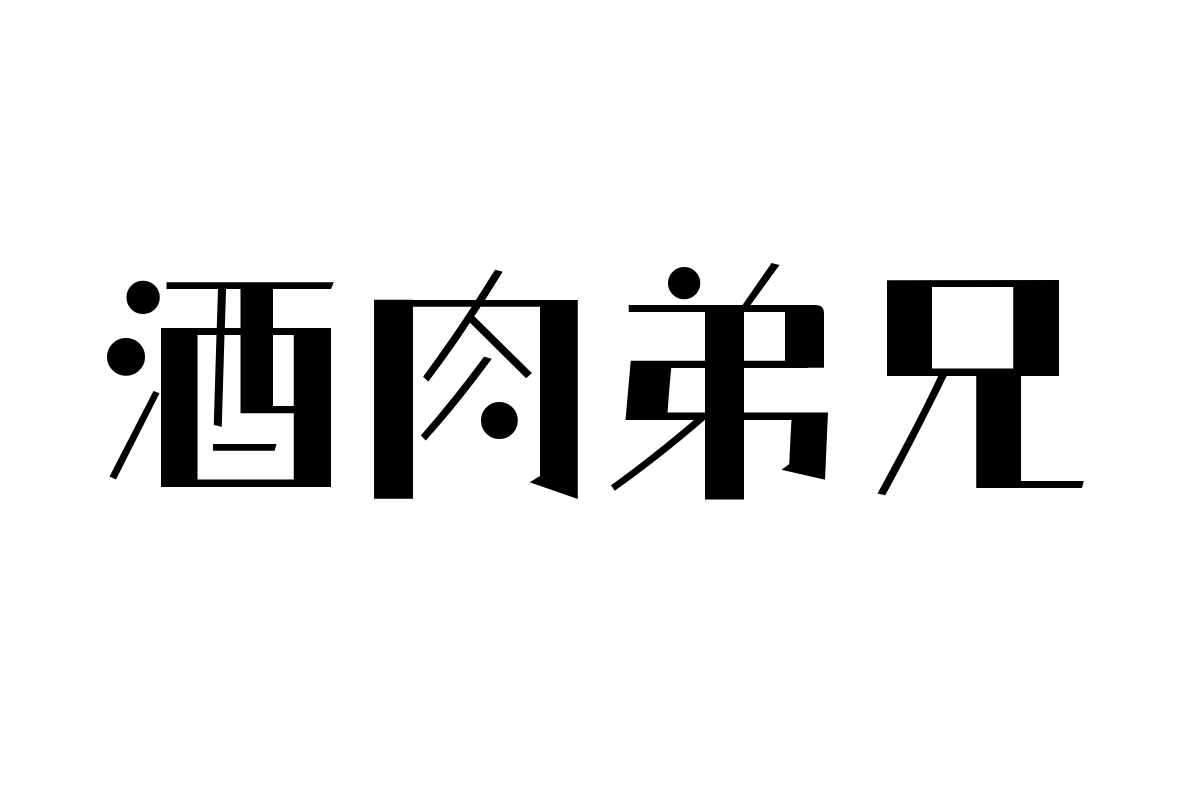
仓耳非白W04是一款由北京仓耳文字技术有限公司出品的免费可商用字体。以下是对该字体的详细介绍:
1. **字体特点**:
– 仓耳非白W04是一款粗细对比明显、风格强烈的字体,拥有5个字重的版本。
– 结构方整,笔形简洁利落,带有区别于其他字体的风格。
– 设计时注重字形转折处直角处理,撇捺等笔画也以直线呈现。
2. **字体家族**:
– 仓耳非白W04属于仓耳字库的家族字体之一,共有22款免费商用字体。
3. **使用场景**:
– 该字体适用于需要强烈视觉对比和独特设计风格的广告、标志、海报等设计场合。
综上所述,仓耳非白W04是一款具有鲜明个性和强烈视觉效果的免费商用字体,适用于多种设计场景,特别是需要突出对比和风格的商业项目。